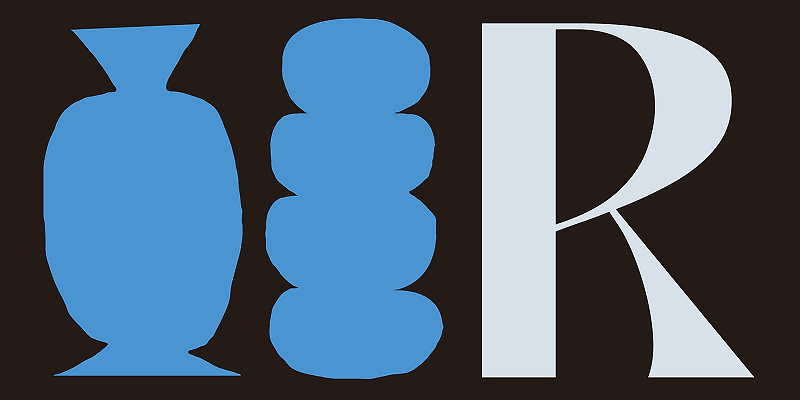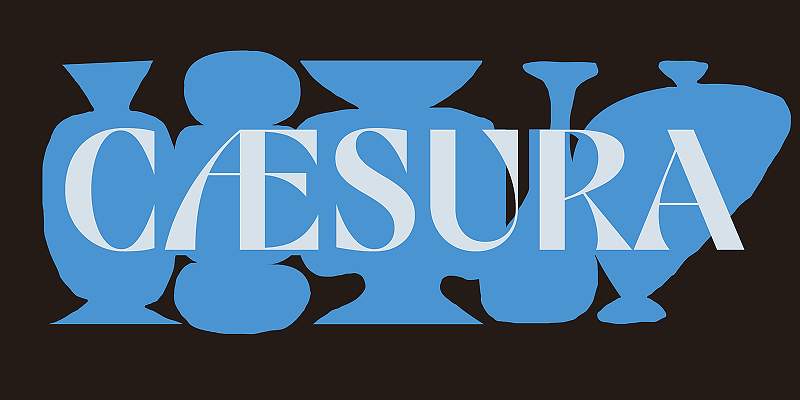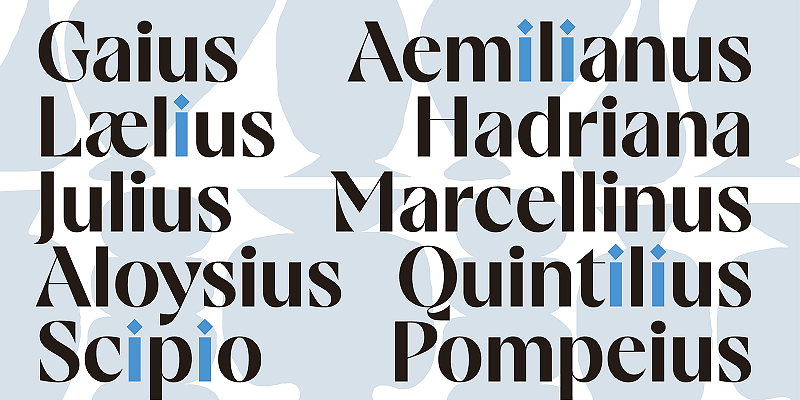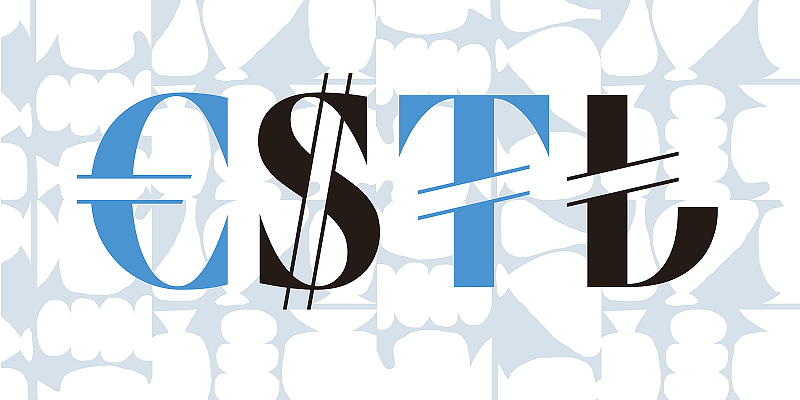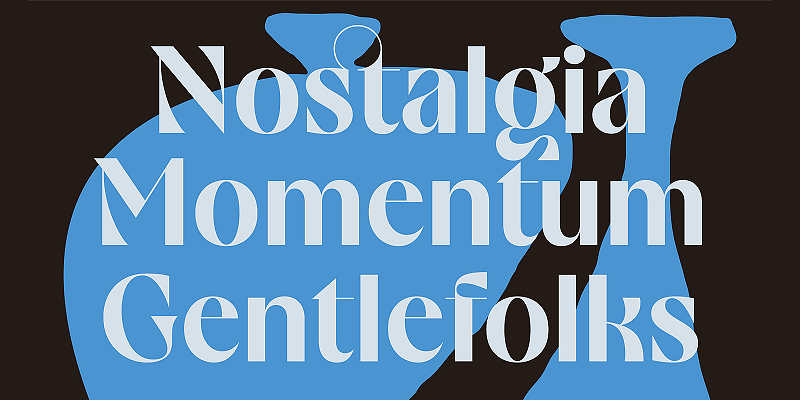
Cæsura est une police d’affichage à contraste élevé, fusionnant des styles de lettrage issus de la signalétique européenne du milieu du XXe siècle et de la calligraphie japonaise. Disponible en une seule graisse au caractère affirmé, elle présente des traits exagérés, des fioritures et des formes acérées, équilibrant structure et expressivité pour un impact visuel fort. Ses proportions raffinées et ses détails subtils la rendent idéale pour les contenus éditoriaux, les marques et les interfaces utilisateur où une typographie sophistiquée est recherchée.